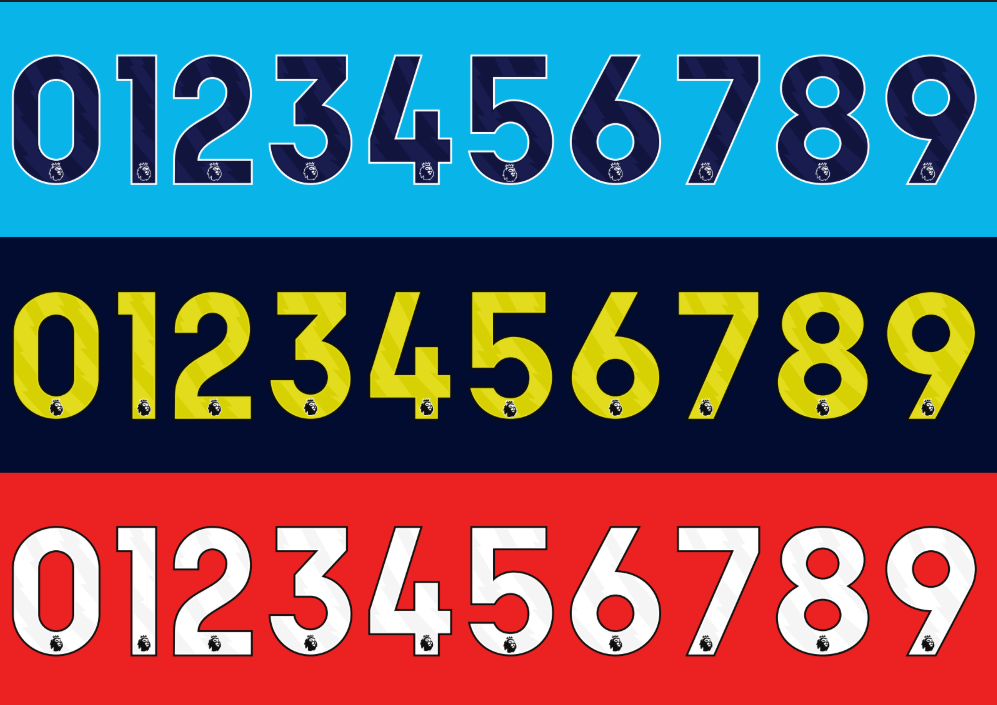
Quando falamos da elite do futebol mundial, a Premier League é insuperável. Seja nos gramados do Etihad Stadium ou em Anfield, a identidade visual do Campeonato Inglês é unificada e inconfundível. Para a temporada 2025/2026, a liga mantém seu padrão de excelência visual, obrigatório para todos os clubes, desde os gigantes como Manchester City, Liverpool e Arsenal, até as surpresas que sobem da Championship.
Estilo Visual e Aplicação
A fonte da Premier League é famosa por seu design moderno, limpo e altamente legível, desenvolvido em parceria com a Avery Dennison. O estilo visual prioriza a clareza para a transmissão em 4K, com números robustos e letras com curvas suaves, mas imponentes.
É uma tipografia “Bold Sans-Serif” que transmite profissionalismo e energia. Ela é usada exclusivamente nas costas das camisas (nome e número) e nos calções de todas as 20 equipes da competição. Se você quer replicar a autenticidade de uma camisa do Chelsea, Manchester United ou Tottenham, o uso desta fonte exata é obrigatório.